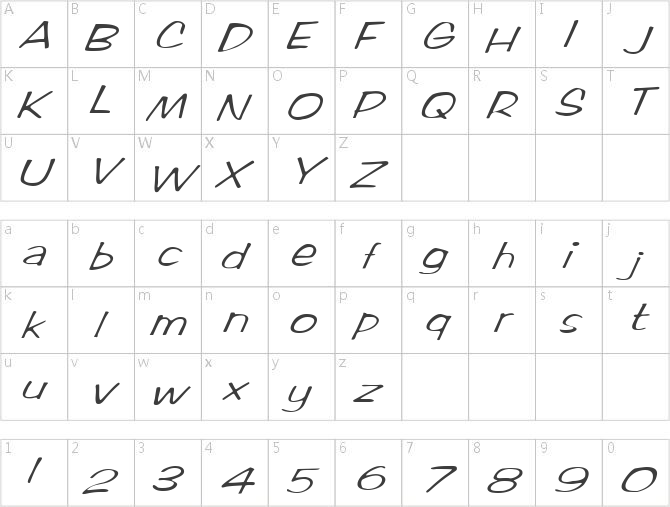
FZ HAND 2 ITALIC 詳情頁
FZ HAND 2 ITALIC
FZ HAND 2 ITALIC介紹
FZ HAND 2 ITALIC字體字庫是一款讓人賞心悅目、百看不厭的英文字體,適合各類廣告和產品包裝設計應用,字體大小0.05MB,格式為ttf字體,上傳用戶是小北,作者/版權方為未知